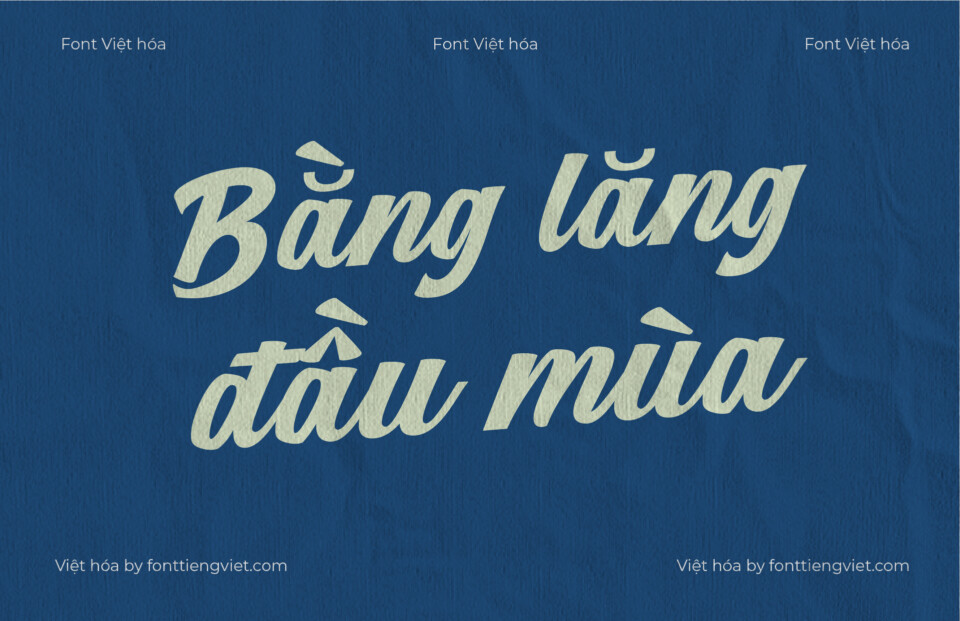
Font Việt hóa 1FTV VIP Longevity – Bộ font chữ sang trọng cho thiết kế Việt
Giới thiệu về Font Việt hóa 1FTV VIP Longevity
Trong thế giới đồ họa hiện đại, việc lựa chọn một bộ Font Chữ phù hợp đóng vai trò quyết định đến sự thành công của một tác phẩm nghệ thuật. Font Việt hóa 1FTV VIP Longevity nổi lên như một lựa chọn hàng đầu cho những ai đang tìm kiếm sự kết hợp hoàn hảo giữa nét cổ điển và hơi thở đương đại. Đây là bộ font được tối ưu hóa hoàn toàn cho bảng mã tiếng Việt, giúp người dùng loại bỏ nỗi lo lỗi hiển thị dấu khi thiết kế các ấn phẩm quan trọng.
Ưu điểm nổi bật của bộ Font Việt hóa 1FTV VIP Longevity
Thiết kế thanh lịch và tinh tế
Đúng như tên gọi Longevity, bộ font này mang ý nghĩa về sự trường tồn và bền bỉ qua thời gian. Các đường nét trong Font Việt hóa 1FTV VIP Longevity được trau chuốt tỉ mỉ với độ tương phản cao giữa nét thanh và nét đậm. Điều này tạo nên cảm giác quý phái, rất phù hợp cho các tiêu đề lớn, thiệp mời cao cấp hoặc các dự án nhận diện thương hiệu sang trọng. Đối với học sinh và sinh viên, đây là công cụ đắc lực để làm nổi bật các trang bìa báo cáo hay slide thuyết trình.
Khả năng ứng dụng đa dạng
Tổng kết về trải nghiệm sử dụng font chữ